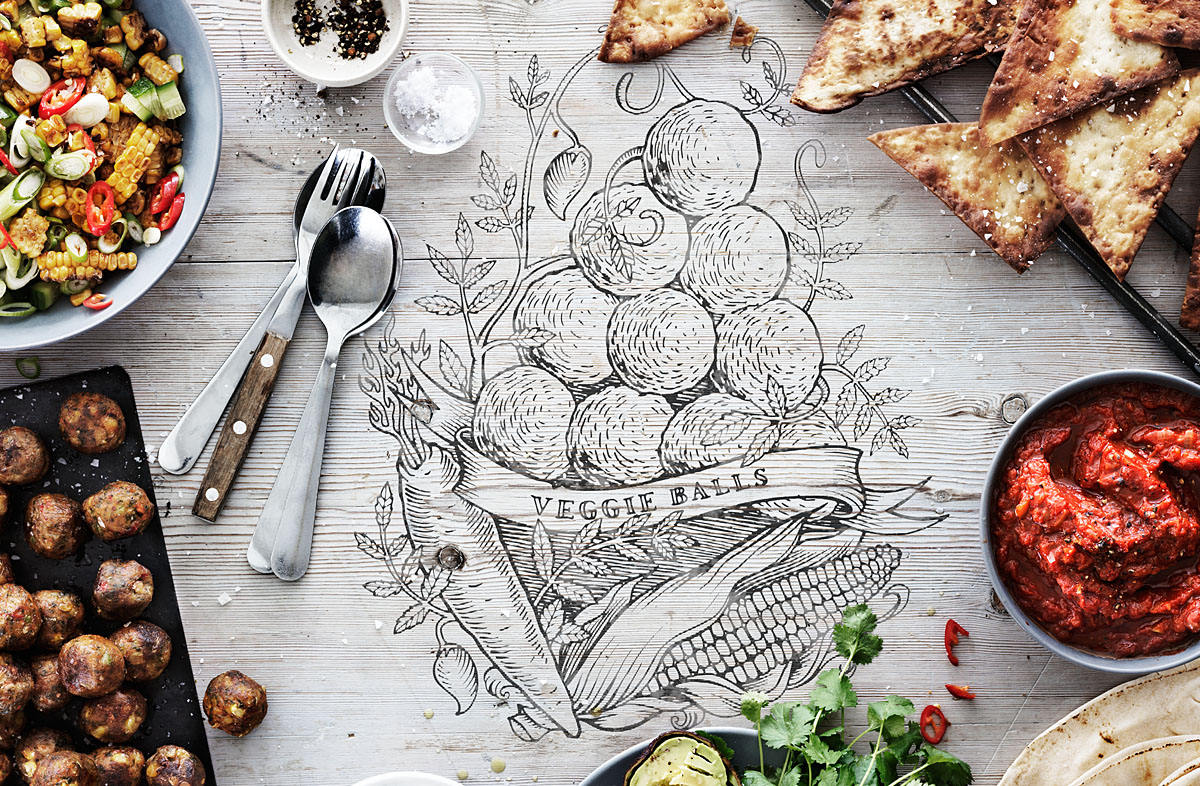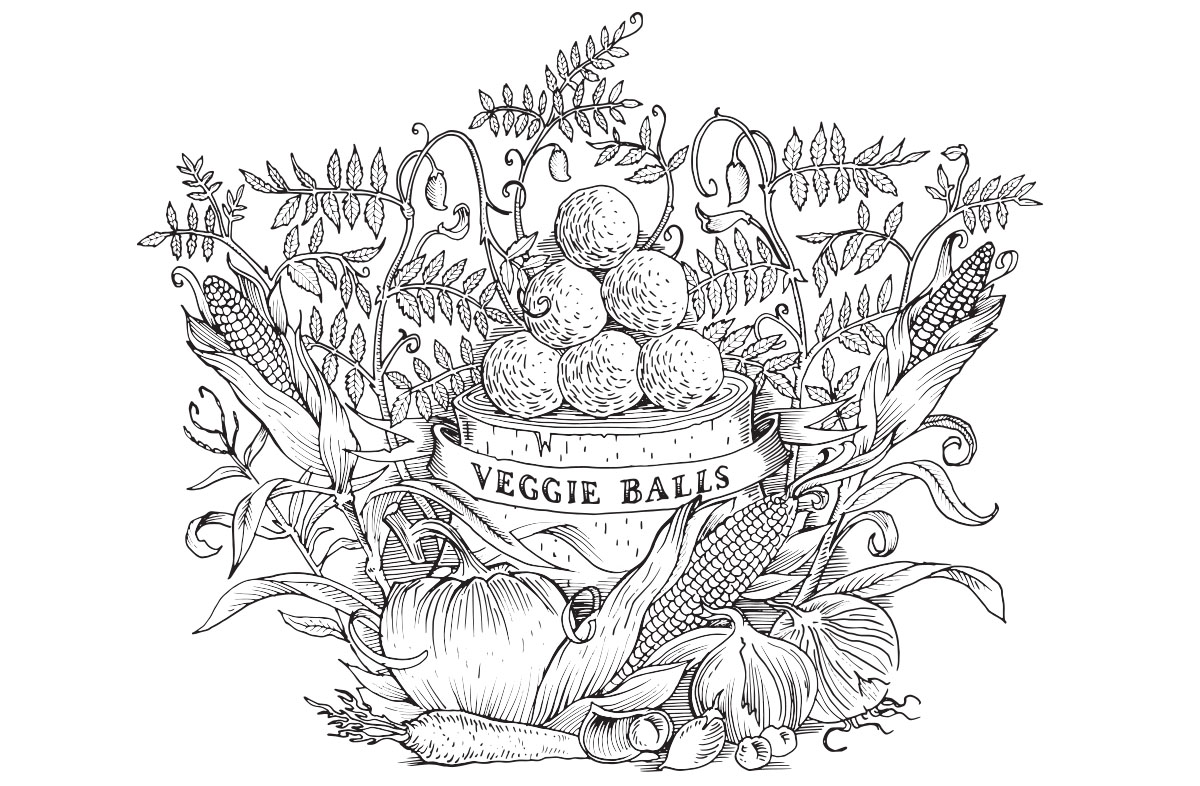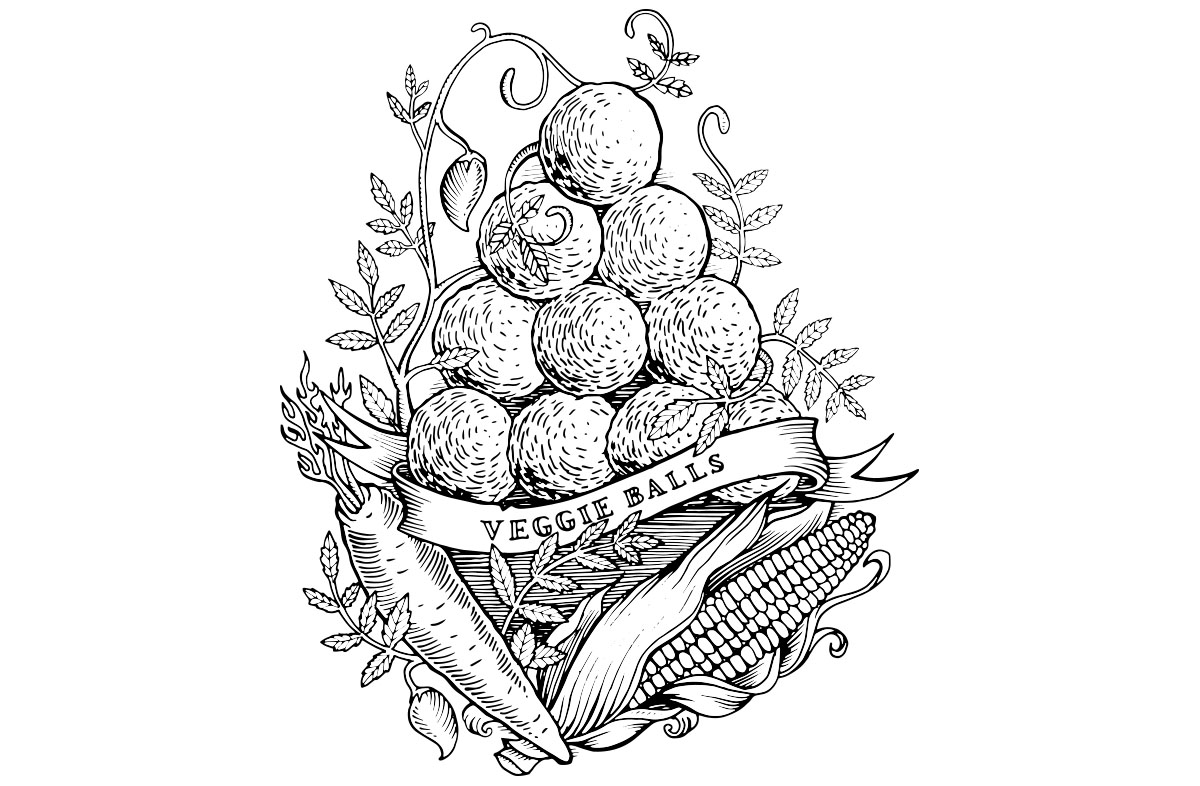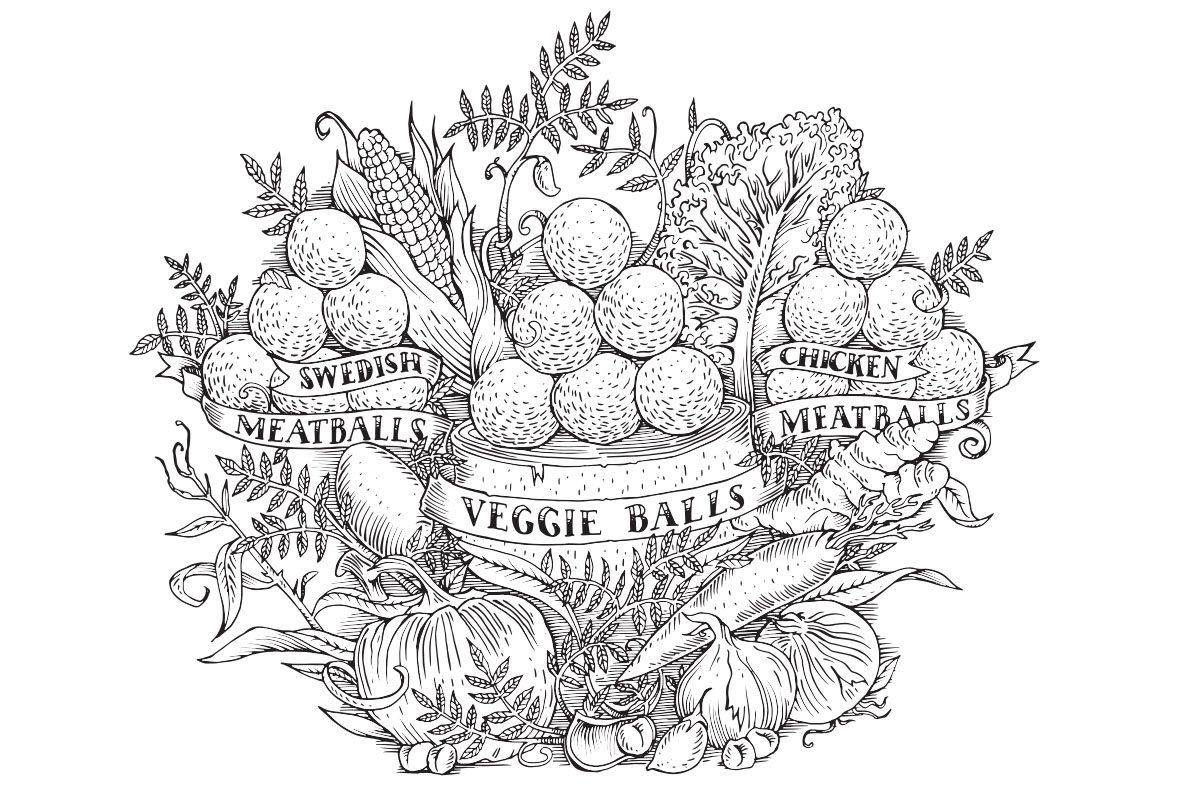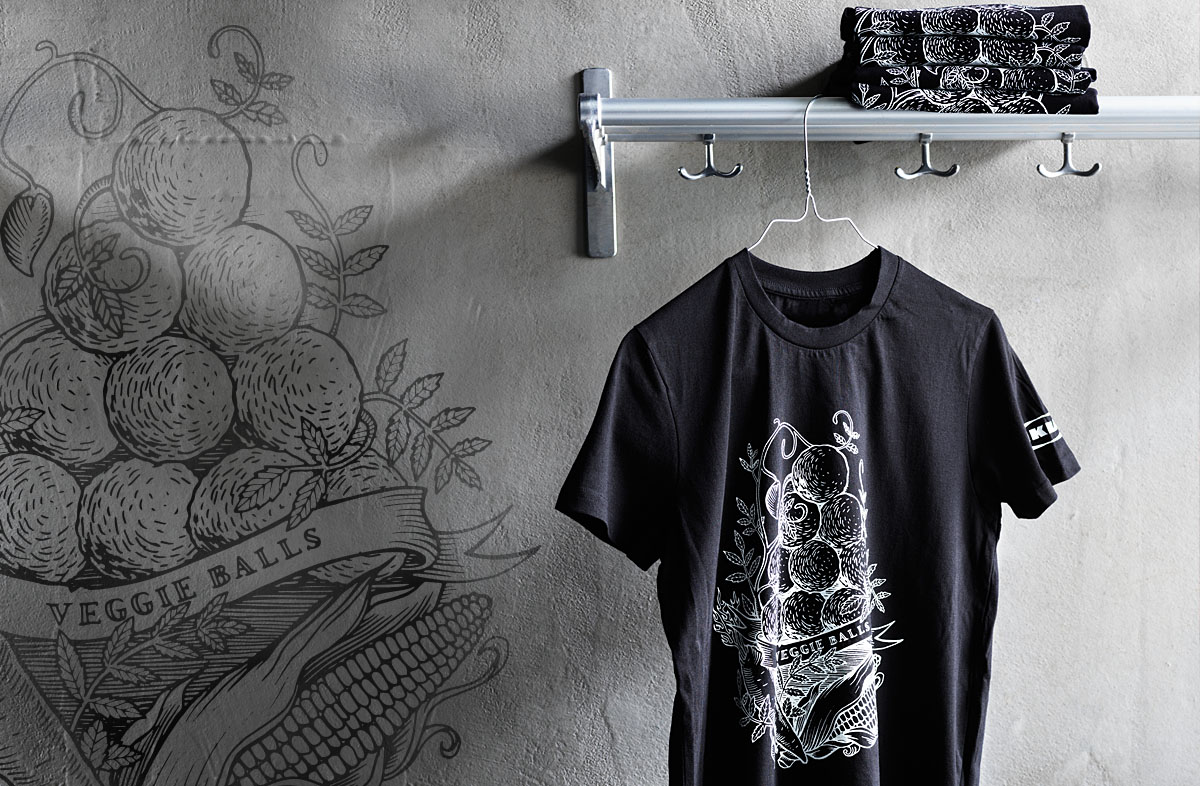
Illustrationerna används i material för att marknadsföra de nya veganska köttbullarna och kläder till personalen. Allting är handritat och skräddarsytt av Alexander Ristori och Oskar Dahlqvist på DQ. Ett tillvägagångssätt som bidrar till hantverkskänslan som de nya veganska köttbullarna har, enligt byrån.